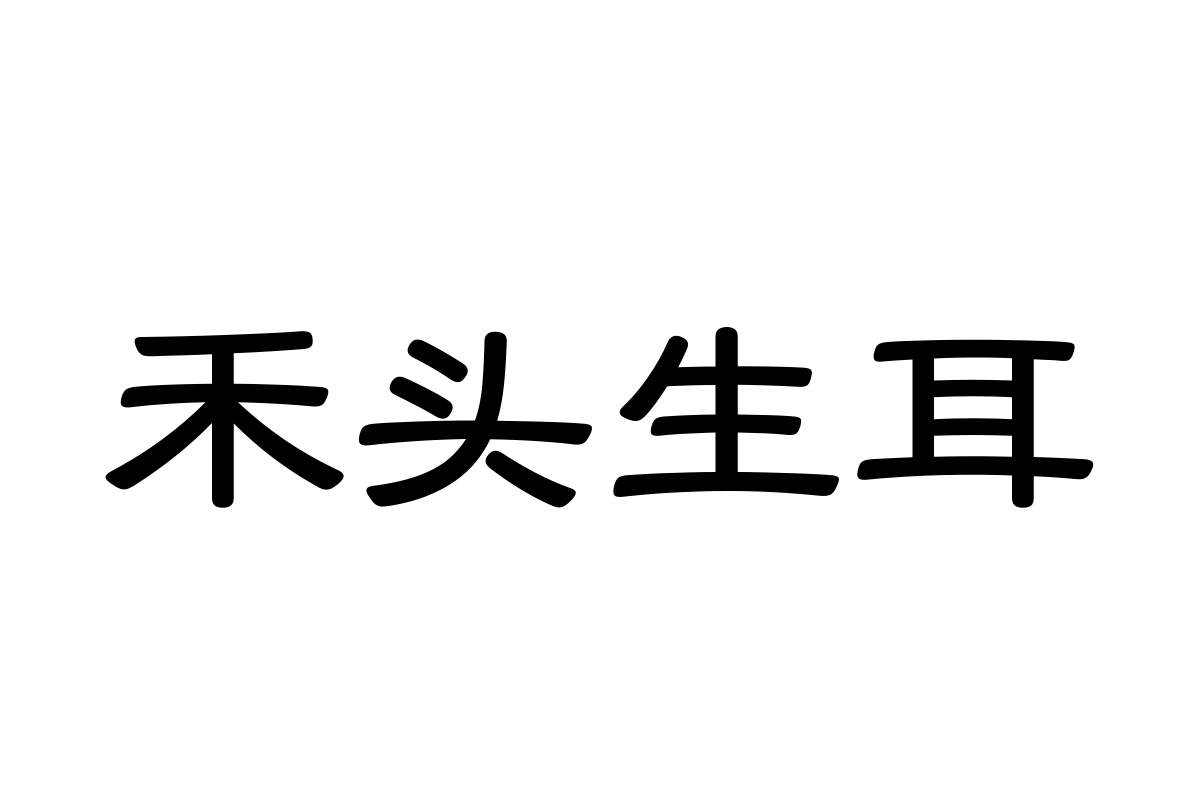
汉仪玉筋隶65是一款专为中文书写设计的字体。它采用了传统的隶书风格,线条流畅而有力,具有很高的辨识度和艺术价值。这款字体适用于各种中文文档、广告、海报等场景,能够为作品增添一种古典的韵味和美感。
字体特点:
1. 线条流畅:字体中的笔画线条流畅自然,给人一种优雅的感觉。
2. 结构规整:字体的结构规整有序,每个字的笔画都按照一定的规则排列,使得整体看起来更加和谐。
3. 易于识别:字体中的每个字都清晰可辨,便于阅读和理解。
4. 适用范围广泛:这款字体适用于各种中文文档、广告、海报等场景,能够满足不同用户的需求。
总之,汉仪玉筋隶65是一款非常适合中文书写的字体,无论是用于设计还是印刷,都能够展现出独特的魅力和效果。